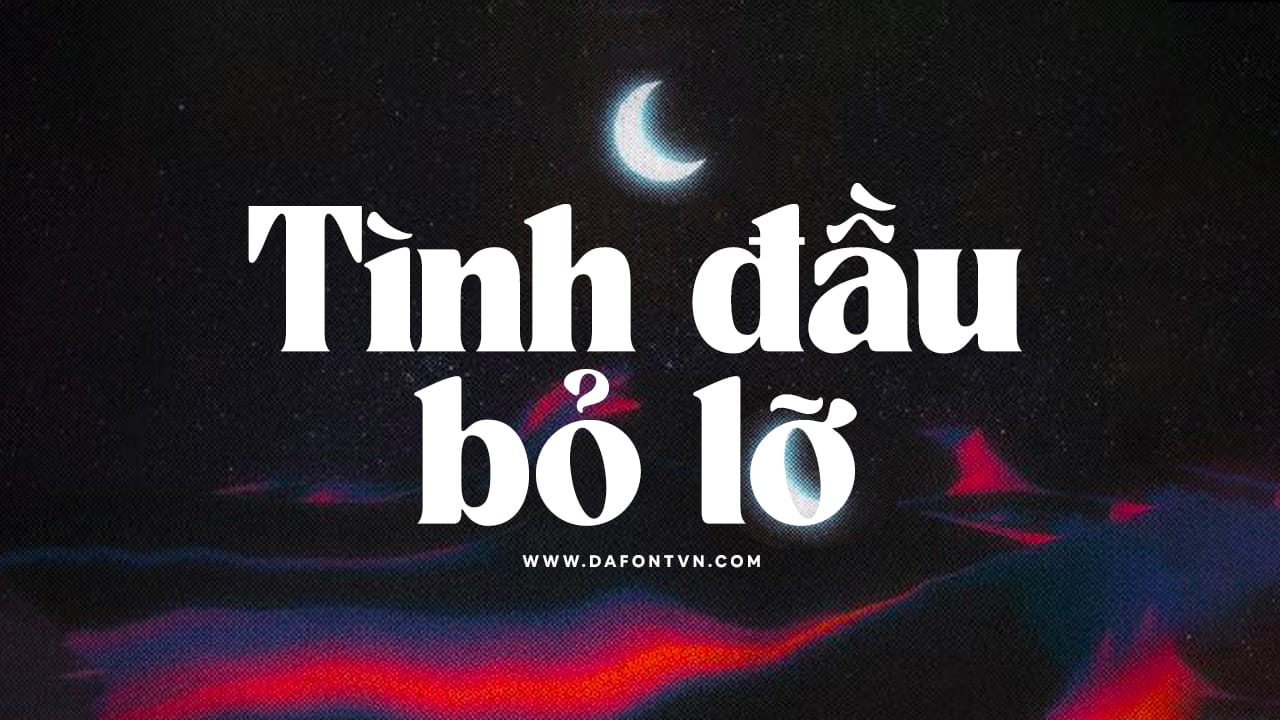
TAN – NIMBUS là một kiểu chữ lấy cảm hứng từ psychedelic. Một phong cách retro, ấn tượng, nổi bật và vui tươi. Với các nét chữ được thiết kế đậm, dày, các nét chữ in hoa được vẽ uốn cong mềm mại ấn tượng ở đầu hoặc cuối mỗi chữ cái.
Phông chữ này hoản hảo để sử dụng làm tiêu đề, bìa sách, tạp chí, thiệp mời, quotes hoặc bất kỳ thiết kế nào khác cần một phông chữ vừa mang hướng cổ điển và hiện đại.
Font TAN – NIMBUS việt hóa đầy đủ. Ngoài ra, vì các dấu của font gốc khá nhỏ vì vậy mình đã sửa lại các dấu và ký tự cho to, rõ ràng hơn để hiển thị tốt nhất ở các kích thước khác nhau.